字体的使用和应用在营销和设计的交织世界中扮演着重要角色。字体设计可能会对观众产生重大的心理影响,并影响他们对品牌及其产品的看法。也许在网络上尤其如此,在网络上,正确的字体可以使所传达的消息具有一定的信誉和永久性。
字体和字体组合的正确选择在很大程度上取决于项目类型,还取决于设计人员的技能。在日常工作中使用预先设计的字体的网络和图形设计师需要了解排版的要点,以便为每篇作品选择最佳字体。另一方面,专业的字体设计师可以为特定项目创建自己的自定义字体,并使每种字体的样式适应项目的目的。
当我们谈论优雅字体时,通常是指同时复杂,豪华和经典的字体。在本文中,我们将共享一组优雅的字体,这些字体可以免费使用,并且可以应用于多种环境。
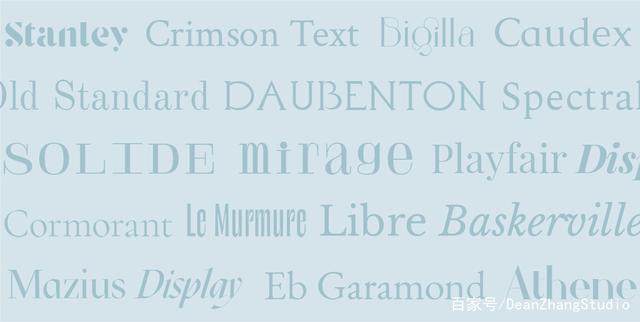
衬线字体
衬线字体主要用于大块文本,尤其是在书籍和报纸中。多亏了衬线,也就是字母末尾的小笔画,这种字体显得特别传统,精致和精致。
1. EB GARAMOND
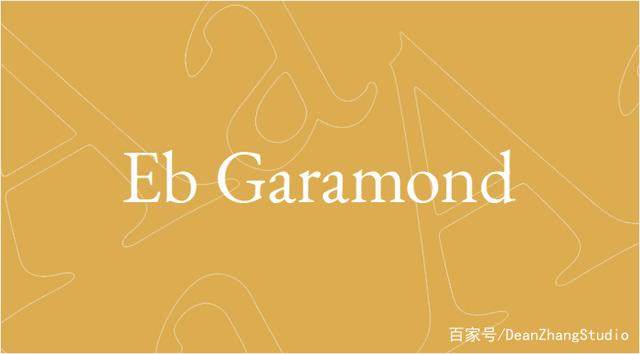
Garamond字体被公认为16世纪法国文艺复兴时期风格的最明显代表,并且是全球排版的关键字体之一,其优雅的形式和出色的可读性使其易于识别。EB Garamond代表着这种风格的复兴,并在很大程度上依赖于1592年在Egenolff-Berner标本中发现的字母形式,因此得名。
许多字体设计师最近都试图使Garamond复兴,但是没有哪一种字体比EB Garamond更具通用性。除罗马字体外,此字体还具有由著名法国字体设计师罗伯特·格兰洪(Robert Granjon)设计的斜体,希腊和西里尔字母。
EB Garamond由Georg Mayr-Duffner(奥地利字体设计师)于2011年根据开放字体许可发布。这意味着其他人可以使用,但也可以修改字体,这就是向这种类型添加一些OpenType功能的方式,例如斜体大写字母,小数,教科书替代品等。
著名的字体设计师Erik Spiekermann,曾设计Berlin Grotesk,FF Meta Serif,Fira Sans,Nokia Sans和许多其他字体,他将EB Garamond描述为最好的开源字体之一。它的受欢迎程度不足为奇,许多品牌都选择在其项目中使用它
例如,创意代理商Studio Bonny在其正文中使用EB Garamond,这为其网站带来了非常优雅的吸引力。
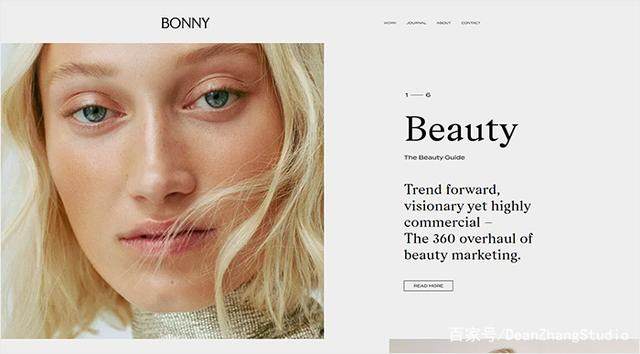
在Qode,我们也喜欢这种字体。在我们的LaComète主题中,我们主要在标题中使用了罗马和斜体字符,这使我们能够突出此商店主题的整体简约感。
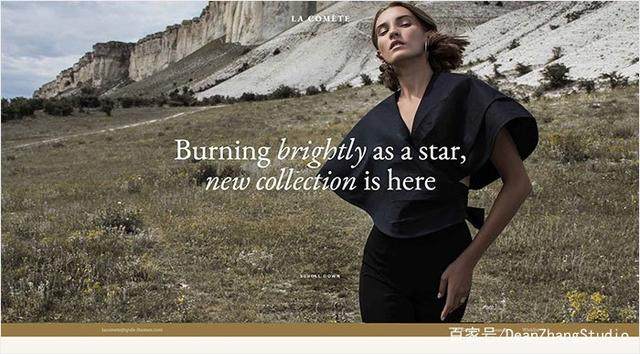
在Fey主题中,我们通过使用较重的字体重量以及标题中的所有大写字母和文本正文中的大胆字母,来实现现代,女性化的外观。
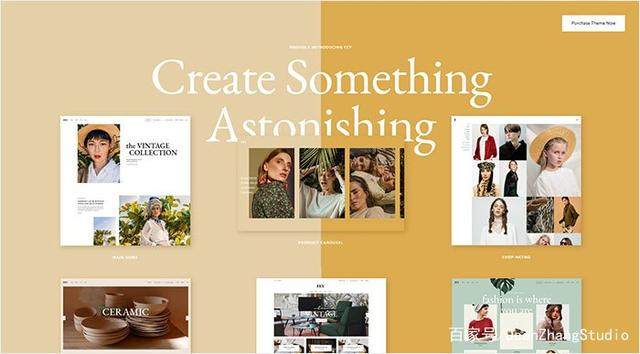
2. PLAYFAIR DISPLAY
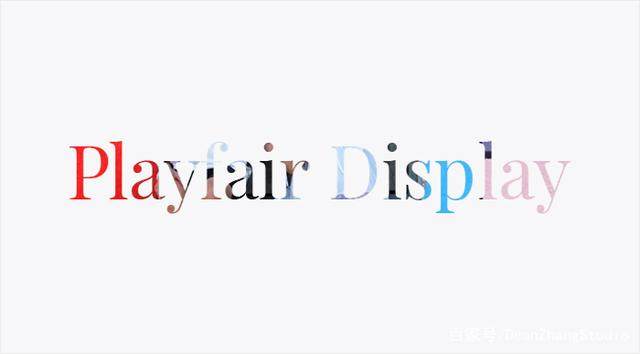
这种过渡字体是由阿姆斯特丹的字体设计师Claus EggersSrensen创作的。Playfair Display是设计师在希望安全玩耍时使用的最常见的优雅字体之一。与一些不太夸张的字体搭配使用时,其高对比度字母和18世纪典型的精致线条变得更加突出。
就像在Penumbra主题中一样,使用此字体的最佳方法是在标题和副标题中。
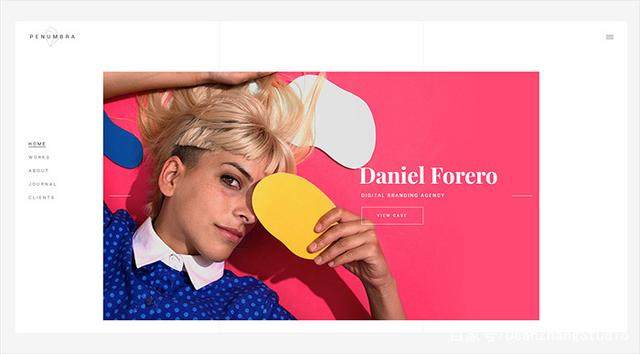
它也可以在大量喜欢印刷的网站上使用,例如Sacha Tourtoulou的网站或Brynn主题,那里的印刷是关键的设计元素之一。
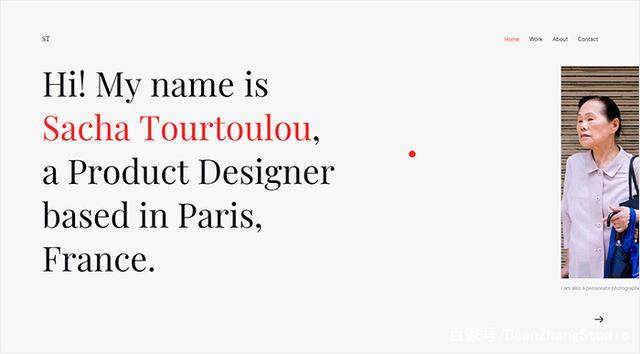
无论您是按常规字体还是斜体字体使用(混合正确的字母间距),Playfair Display的全大写版本都突出显示了该字体的纯粹优雅,如Attika主题所示。
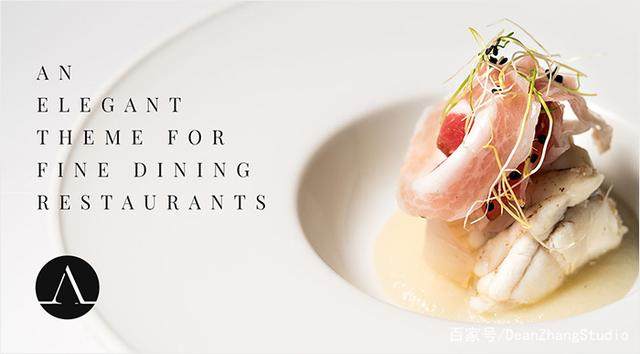
3. CRIMSON TEXT
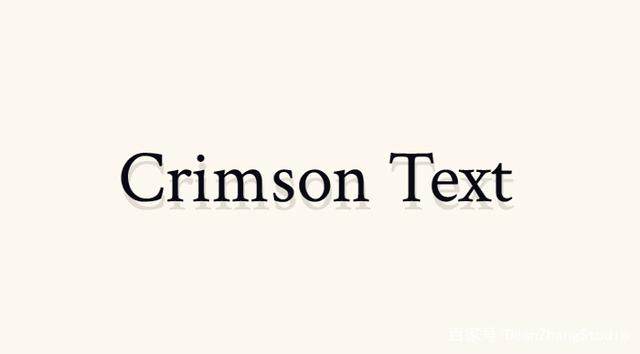
由Garamond字体类型的启发,老字体美丽的身影,而扬齐休,罗伯特·斯林巴奇和乔纳森·霍弗勒,作品最大的特点了的深红文本字体系列是它的功能。
您可以在标头和不太突出的文本中使用它-它易于阅读,外观也很复杂。如Anecdote Candles网站上所见,此字体系列的完美适应性在细节上非常出色,例如使用斜体和所有大写字母时。
正如我们的Roisin主题所展示的那样,较小的斜体字母和更占优势的sans serif字体的组合也非常吸引人
另一个很好地描述了深红色文本(特别是在较小的字体中使用)的网站是Triple Canopy。
另一方面,我们的Bard主题说明了该字体系列在大标题中使用时的外观,这再次证明了其灵活性。
4. OLD STANDARD
是什么让老标准具体是截断和经典的外观字母形状,典型的19世纪末和20世纪初的。这种字体在网络上并不常见,如果您决定在项目中使用它,那肯定是一个勇敢的选择。
马塞尔(Marcel)的网站是文字和标题(粗体变体)中使用的“旧标准”字体的示例。
在Sahel主题中,我们选择了字体最小的方法,并将其专门用于标题。
由于其可爱的形式,这种字体在印刷设计和品牌中很受欢迎。可用它来创建简单的结婚请柬。
5. CORMORANT
这是Catharsis Fonts的Christian Thalmann的主要灵感,他创建了Cormorant类型家族,该家族包含45种字体文件,9种不同的视觉样式(罗马,斜体,婴儿,婴儿斜体,Garamond,Garamond斜体,立式草书,小写和Unicase)和5个权重(轻,常规,中,半粗体和粗体)。他的主要目标是重新设计Garamond并赋予其新的现代外观。他使它适用于印刷媒体和网络,从而确保所有尺寸的印刷品永不过时的优雅。
Calcaterra的网站就是一个例子,说明即使使用得当,这种简洁的字体也可以为品牌的现代和时尚魅力做出贡献。
我们还在ChapterOne主题中选择了该字体,特别是在标题和段落中,并且如您所见,它与主题的精致设计完美匹配。
在Dvi Tylos网站上,作者在正文中使用了Cormorant Garamond,与该奇妙,精美外观的其余部分完全匹配。
Platypus Press,Laura Sauchelli和Creme Guides都基于这种永恒的经典字体来构建自己的网站,这也是每个页面上最突出的元素之一。
在Solene主题中,所有大写字母的标题和斜体字幕的组合都创建了典型的婚礼网站精致外观。
使Cormorant Infant 与Garamond版本的字体区分开来的是略微更具风格的字母形状。而且由于这些形状,仅在文本正文中使用Cormorant几乎是可惜的,因为它们不会像应有的那样突出。
通过强调鸟的独特性和优雅性(以该字体命名),其字母形状的美感熠熠生辉,并在Vasantha Yogananthan的网站上吸引了访问者的注意。此处的文字内容不引人注目,流淌得奇妙。
在Read Wildness网站上,Cormorant Infant更为突出,在那里以极简主义的方式展示诗歌。这强调了形状细密的Garamond风格字母,就像在过去那样,用于写诗,但这次是使用现代技术。
mor Unicase代表小写字体与其他小写字母形状的组合的有趣玩法。在这里,古老的Garamond形状现在具有一种未来派形式,主要用于标题中,如Eola主题所示。
6.LIBRE BASKERVILLE
Libre Baskerville是另一种开源字体,其模仿1941年美国类型创建者Baskerville,它是最受欢迎的经典书籍字体之一,以其精巧和可读性而闻名。Libre Baskerville针对正文进行了优化,它的x高度略高,并且比ATF Baskerville的对比度低,从而确保了更好的屏幕可读性。
在Typozon网站上可以看到其雅致的书本形状,其中斜体,优美的字母主导页面,使它们充满时代感。